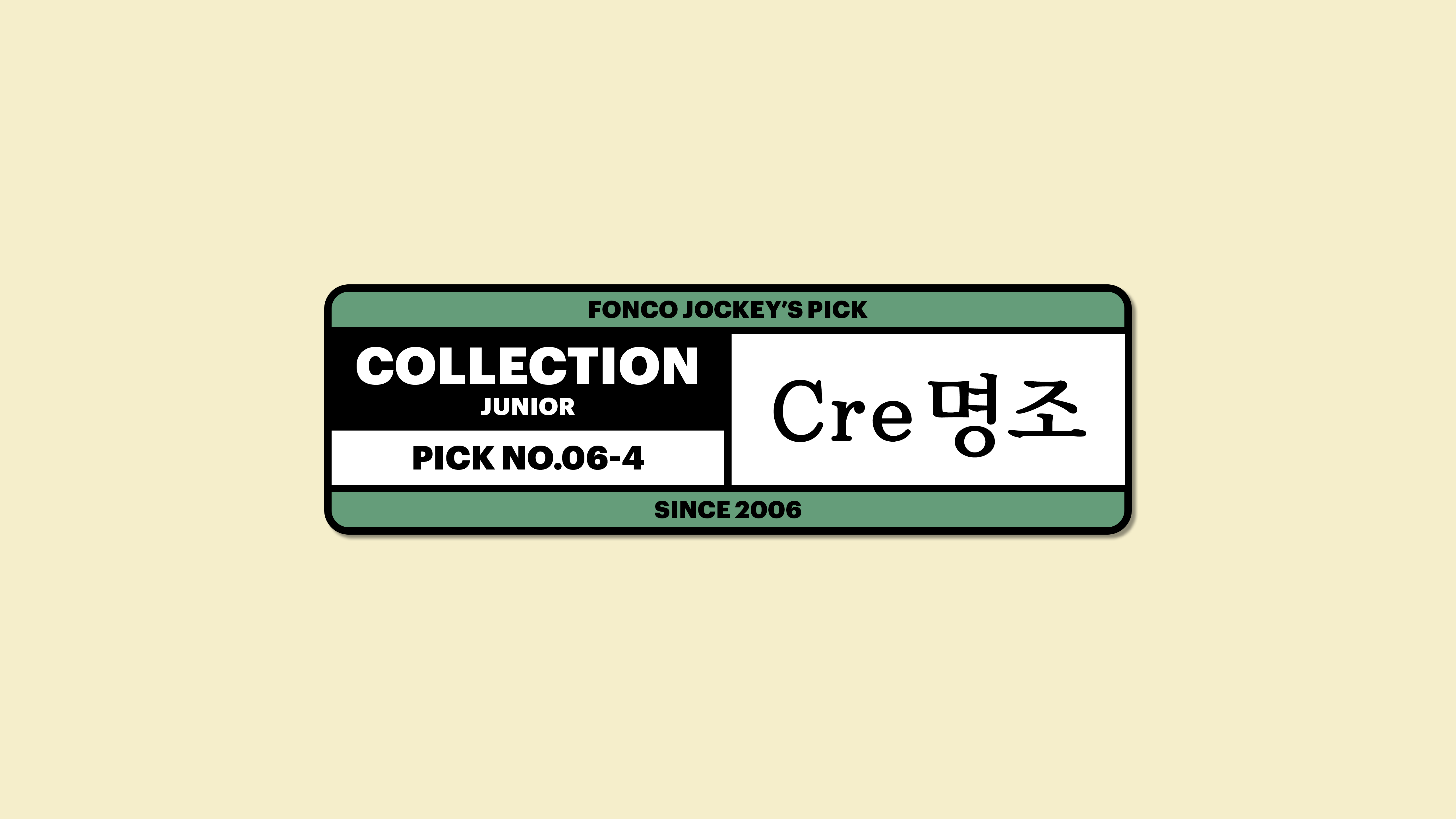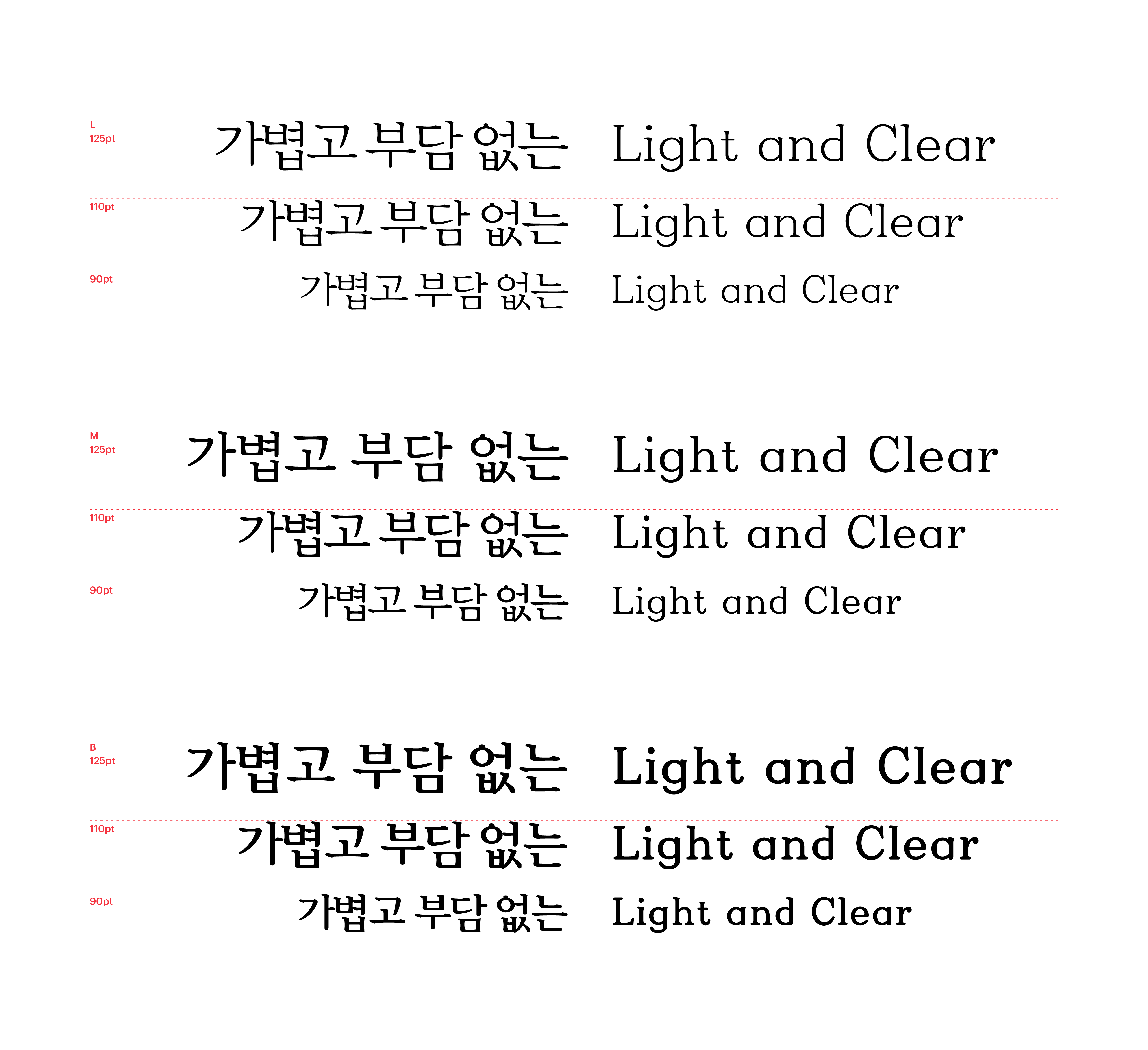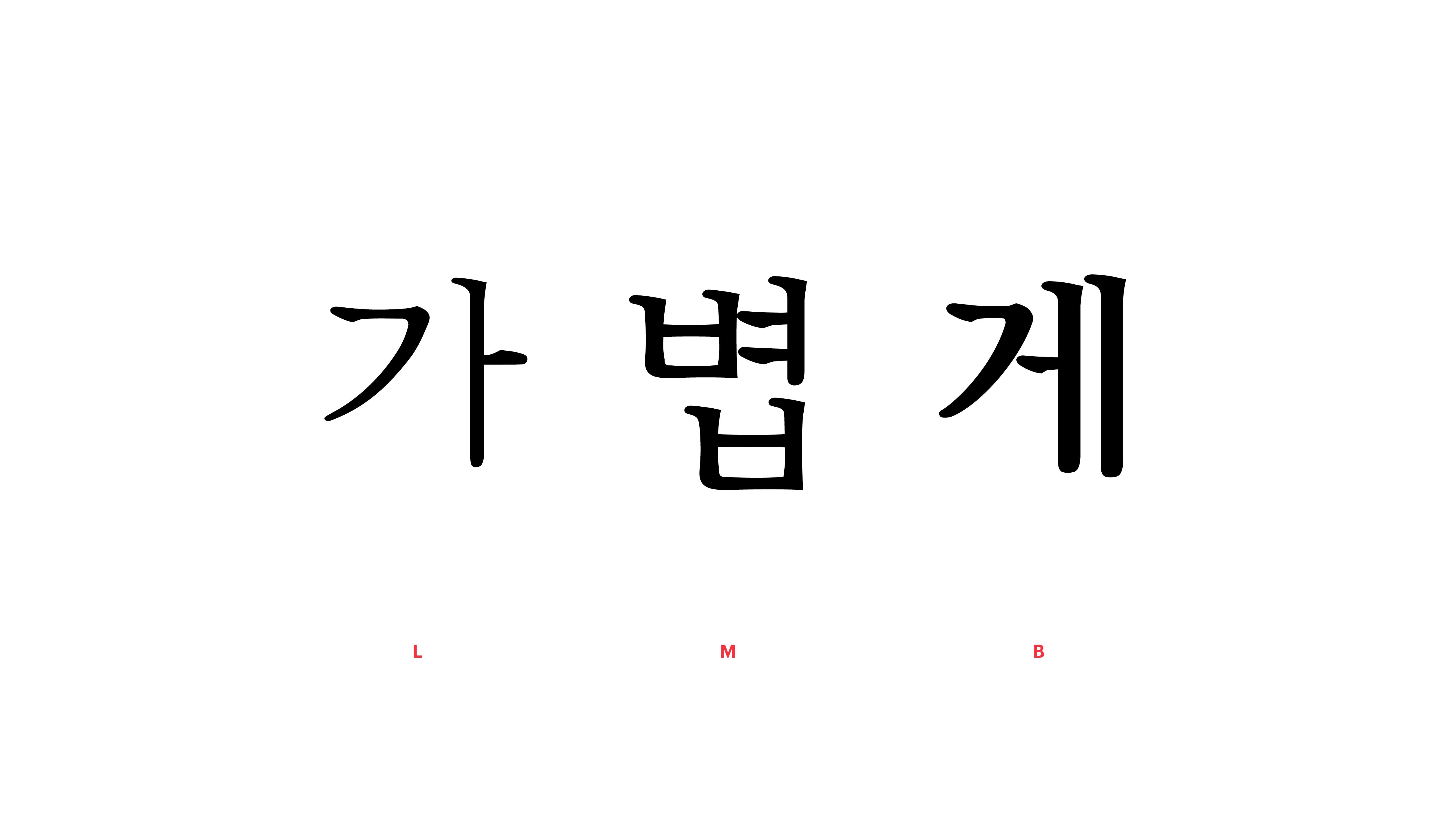
Cre명조
Yoon Cre명조
명조체는 뭐랄까? 가끔 너무 진지해 보이는 것 같아요. Cre명조는 기존의 명조체보다 약간만, 가볍고 부담 없는 명조체를 고민하다 탄생한 폰트랍니다. 글줄의 흐름을 위에 맞춰 가지런히 정돈하고, 획의 꺾임은 최대한 절제하여 적재적소에만 사용했어요. 깨끗하고 한결 세련된 인상을 주는 명조체로 다양한 이야기를 부담 없이 펼쳐보세요.